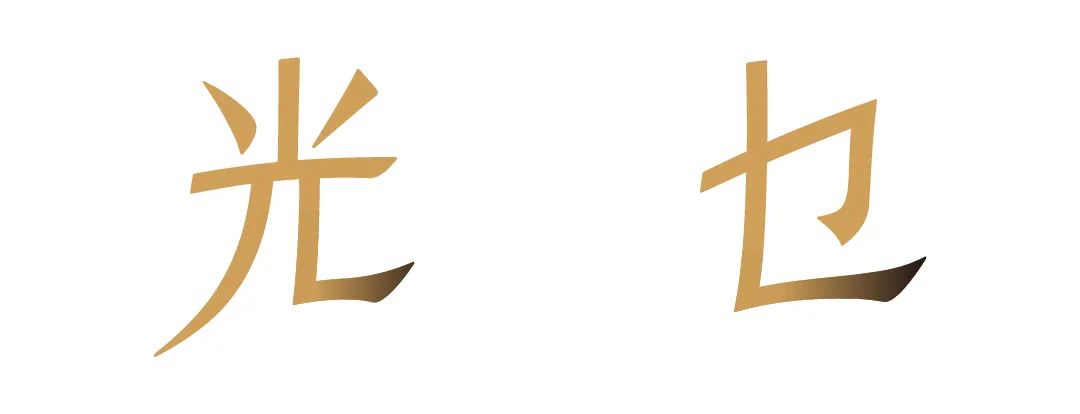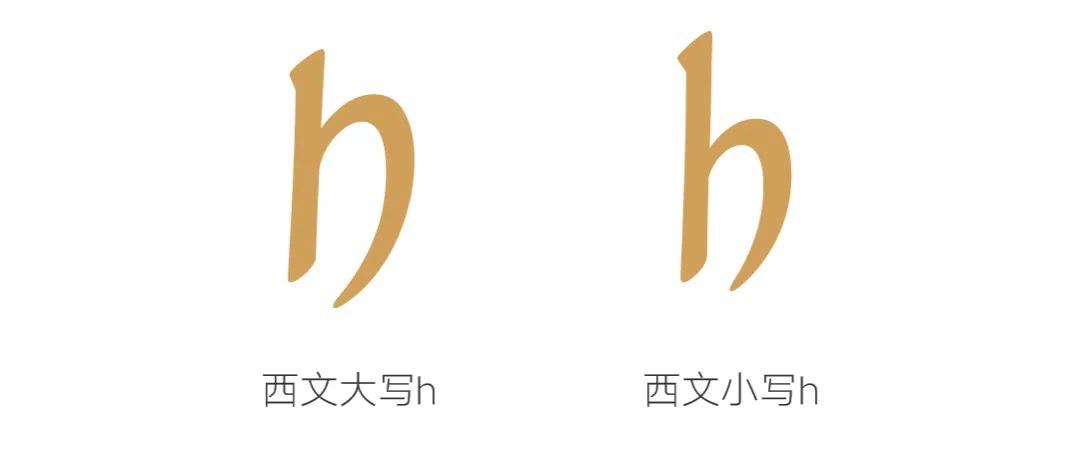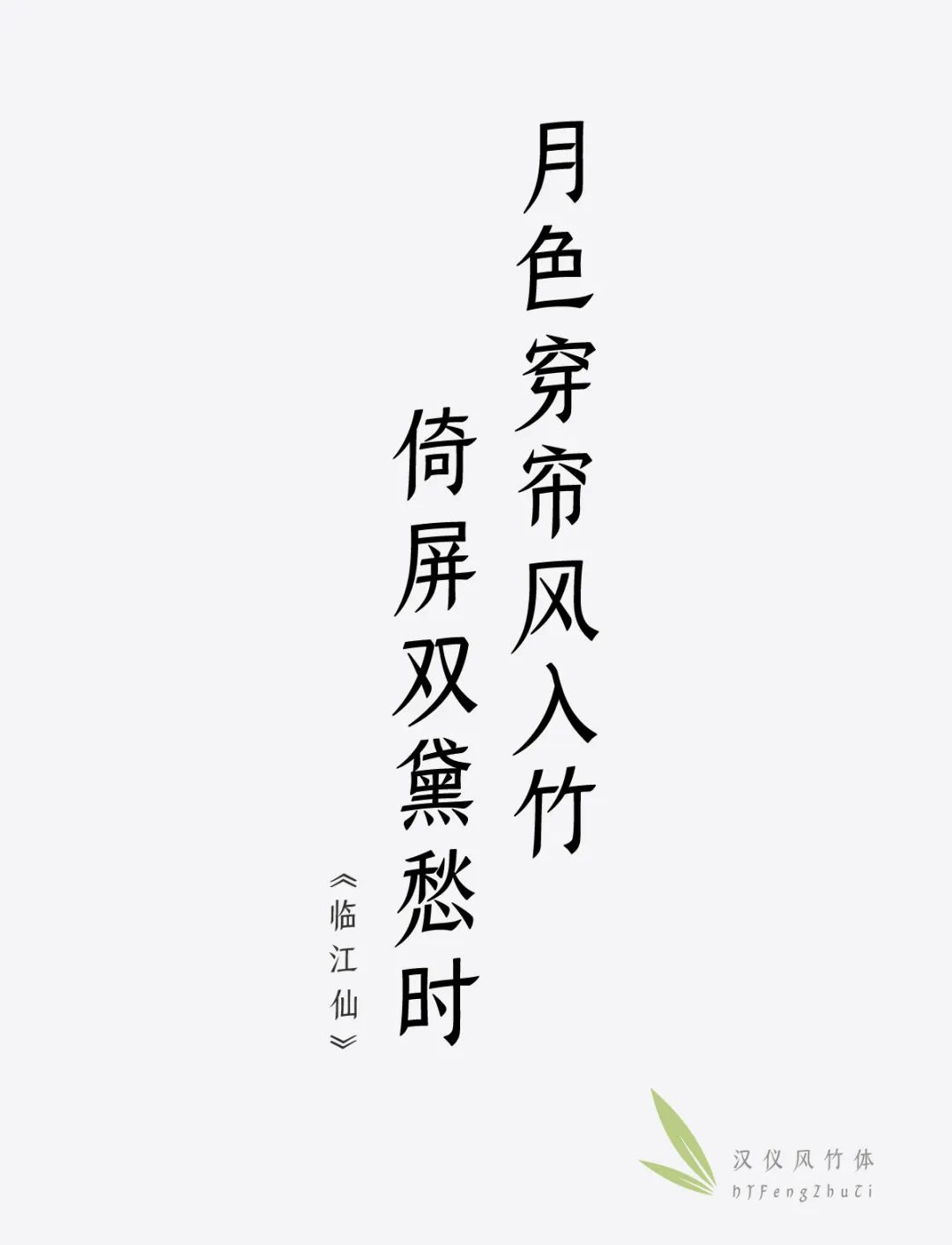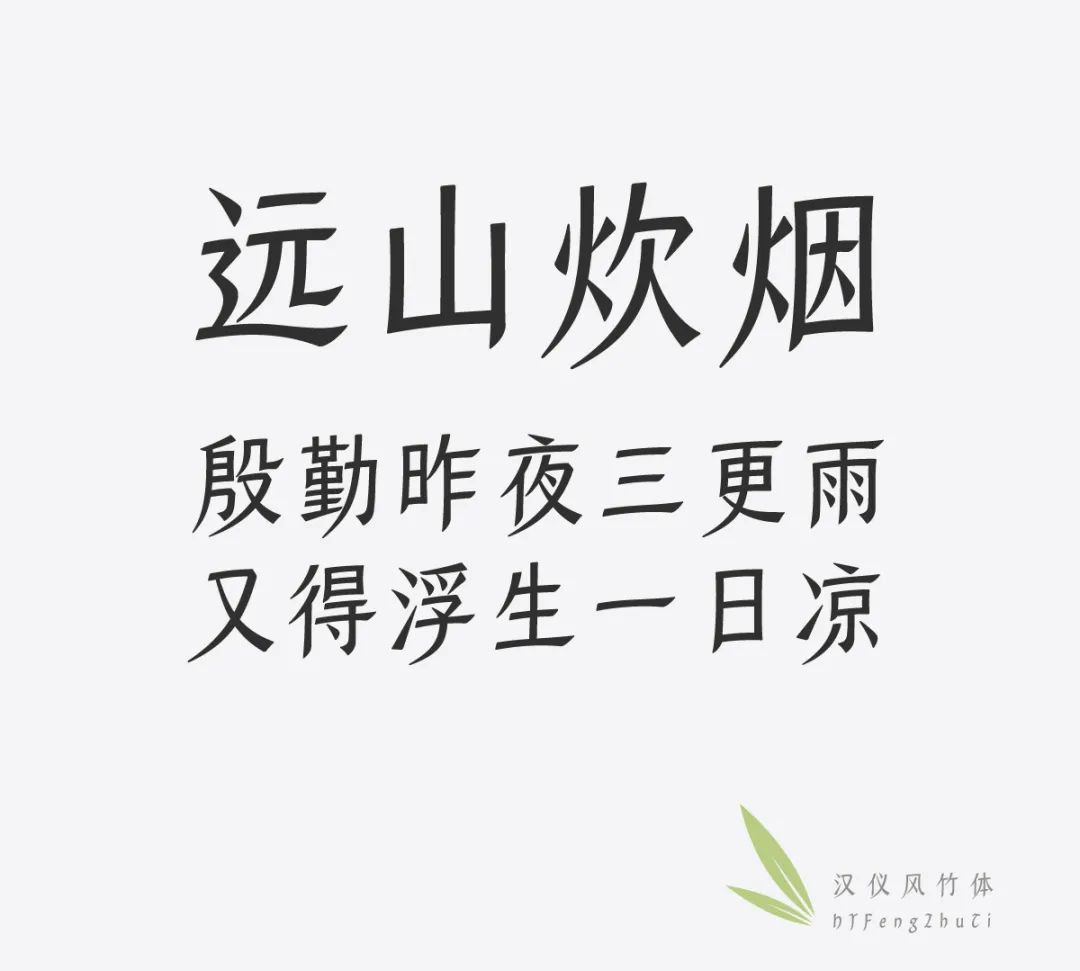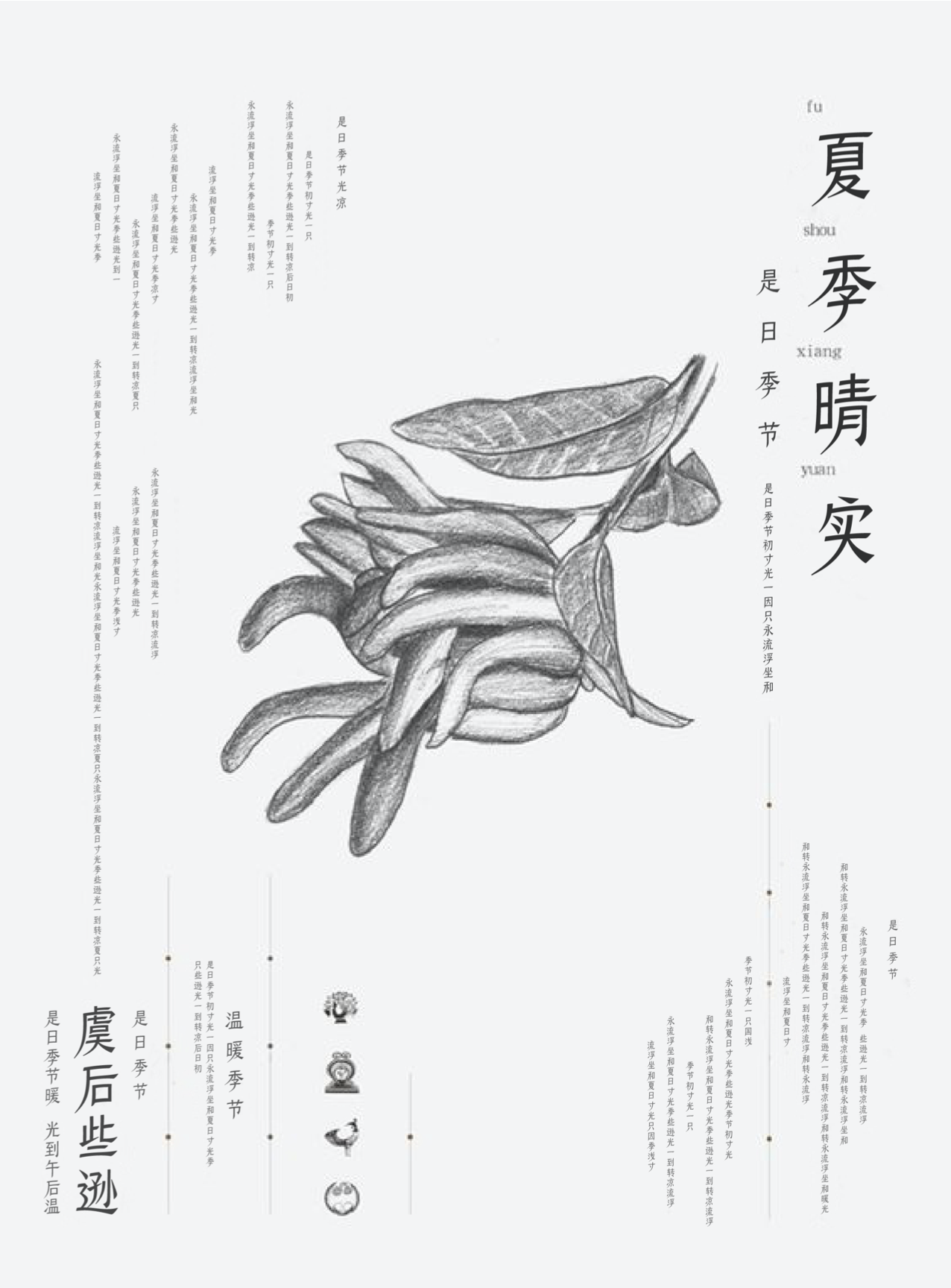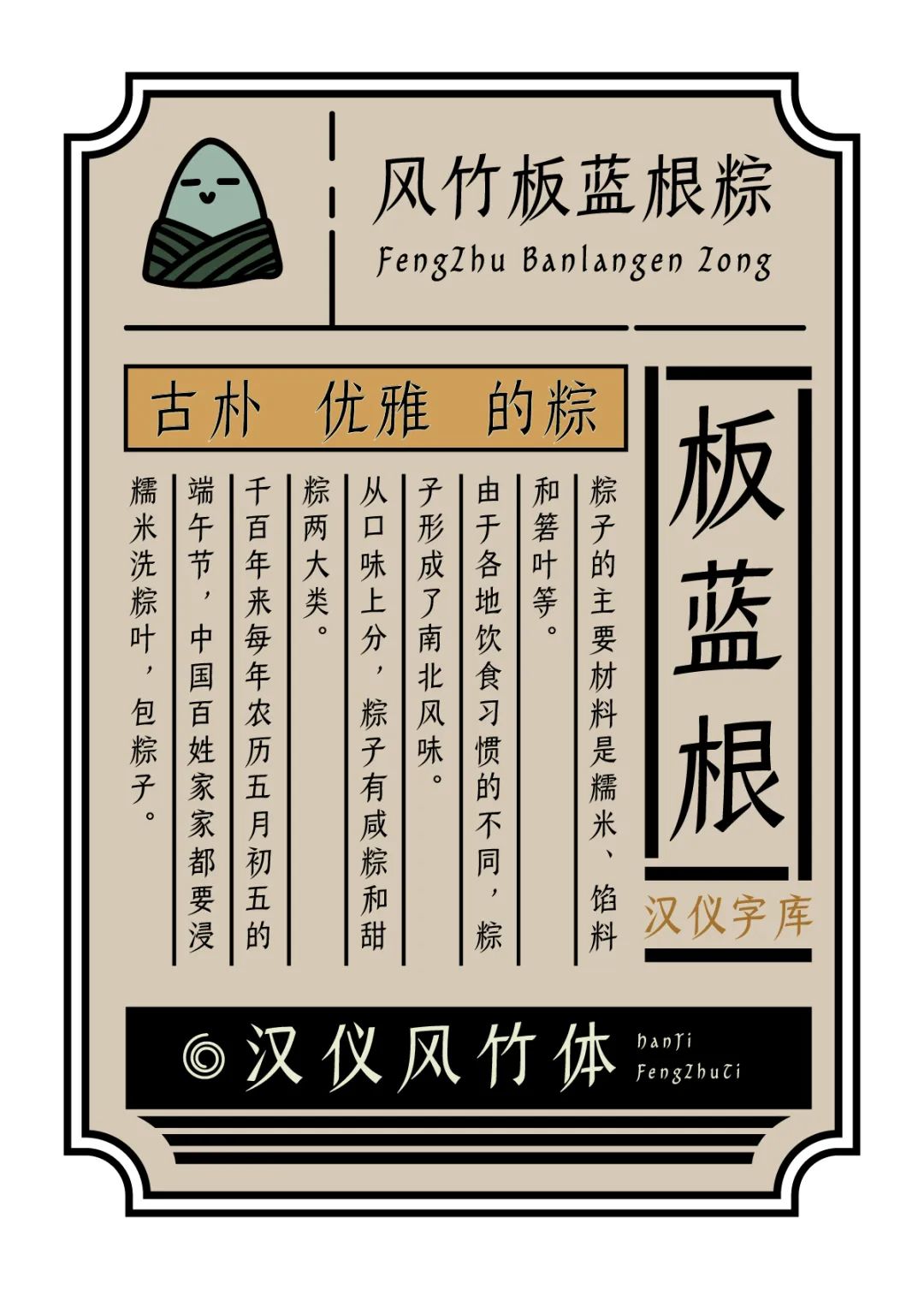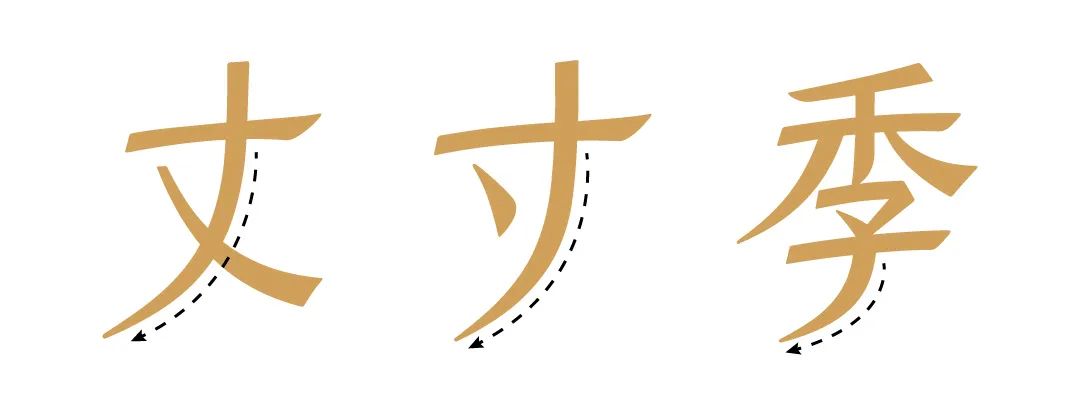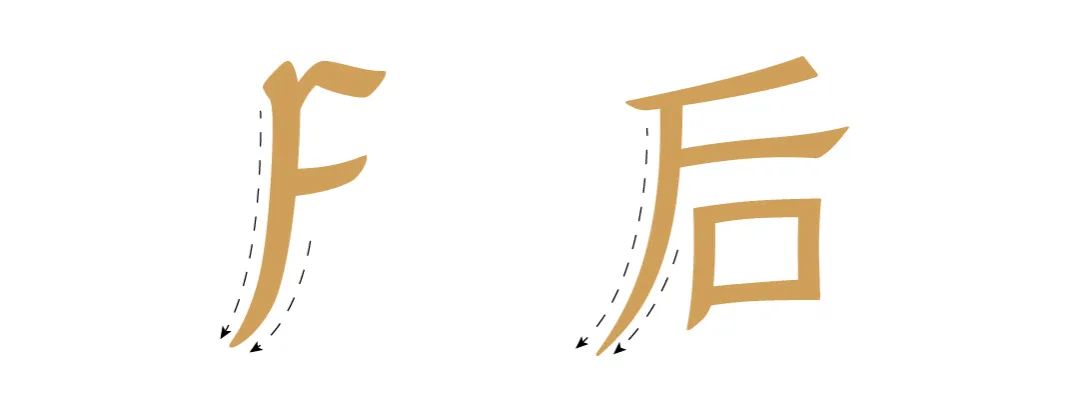
字體名稱: 漢儀風(fēng)竹體
漢儀風(fēng)竹體
漢儀字庫設(shè)計(jì)師:羅夢怡
9169中文簡繁+拉丁字符
漢儀風(fēng)竹體的設(shè)計(jì)靈感來源于漢代簡牘,是快寫篆書向隸書轉(zhuǎn)變的過渡書體。它起源于民間,用筆大膽肆意、任情恣性、不守故常、十分有趣。
漢儀風(fēng)竹體的撇畫是最為個(gè)性張揚(yáng)的筆劃,參考漢簡中順勢而為的感覺,并將漢簡中的夸張之筆都融入到撇畫中,一些豎鉤畫化作撇畫,更加舒展灑脫。
漢儀風(fēng)竹體的鉤畫設(shè)計(jì)保留了由書寫習(xí)慣的重頓和波磔而演化形成的雁尾形式,隨勢賦形這一特征的保留,使其更加舒展。
早期的拉丁字母不分大小寫,最早的書體來自于人們對古羅馬大寫字的模仿,久而久之為了書寫速度才演化出了現(xiàn)在大家熟知的小寫形態(tài)。漢儀風(fēng)竹體的西文設(shè)計(jì)保留了早期的書寫風(fēng)格,別具特色。
漢儀風(fēng)竹體的西文字體主要以Uncial和Carolingian為主。雖然中西文兩款字體的書寫工具不同,字型不同,但是仔細(xì)對比后,卻有許多相似的形態(tài)和感覺,這也是漢儀風(fēng)竹體在做中西文匹配中最有趣的地方。